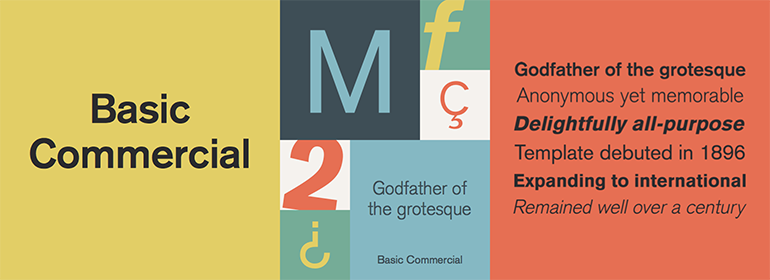
Basic Commercial™
Basic Commercial是一款基于热金属字体时代历史设计的字体。它最初出现在1900年左右,由字体设计师创建,他们的名字没有被记录,但是他们的技能不能被忽视。这种字体的设计在包豪斯、达达主义和瑞士/国际风格的版式大师等各种团体和运动中很受欢迎。它影响了后来各种奇形怪状的字体,如Helvetica和Univers。
Basic Commercial多年来一直以Standard Series的名称在美国发行。字体渗入了日常生活和文化的许多方面;例如,它被选为纽约地铁系统的标识。
Basic Commercial字体家族成员具有清晰和客观的设计。它们的形式几乎没有什么不同寻常之处,但仍然生动而清晰。或许正是这个原因,Basic Commercial的设计在平面设计师中流行了几十年。要了解更多关于字体的历史,如Basic Commercial,请访问我们的字体功能,The Sans Serif Typefaces。此外,这个家族的几种字重也有软而圆的版本可供选择。
Basic Commercial is a font based on historical designs from the hot metal typeface era. It first appeared around 1900, and was created by type designers whose names have not been recorded but whose skills cannot be overlooked. This typeface's design has been popular among groups and movements as diverse as the Bauhaus, Dadaism, and the masters of Swiss/International-Style typography. It influenced for a variety of later grotesque fonts, such as Helvetica and Univers.
Basic Commercial was distributed for many years in the United States under the name Standard Series. The typeface worked its way into many aspects of daily life and culture; for instance, it became the face chosen for use in the New York City subway system's signage.
The Basic Commercial's font family members have a clear and objective design. Their forms exhibit almost nothing unusual, but remain both lively and legible nonetheless. Perhaps for this reason, Basic Commercial's design has been popular with graphic designers for decades. To read more about the history of typefaces like Basic Commercial, visit our font feature, The Sans Serif Typefaces. In addition several weights of this typefamily are available as soft rounded versions."